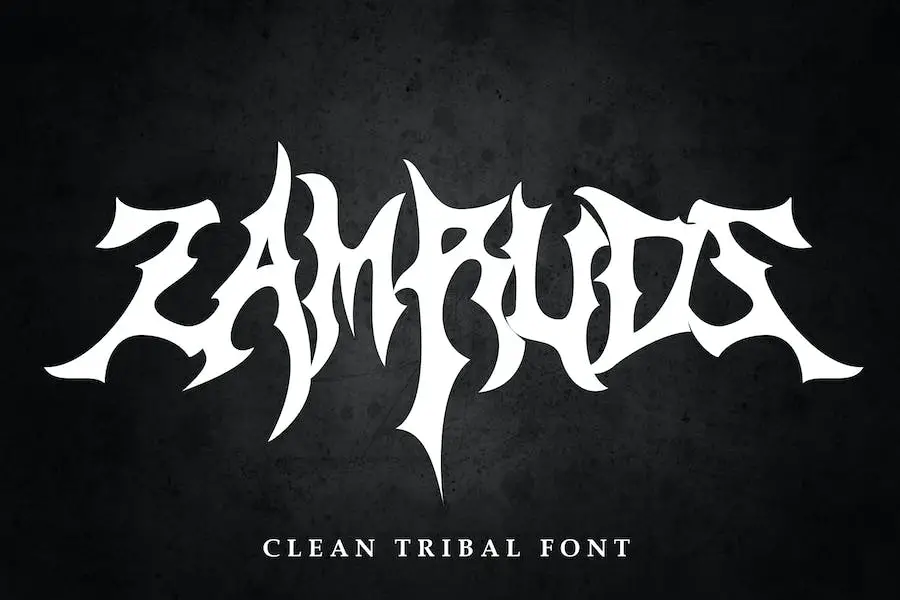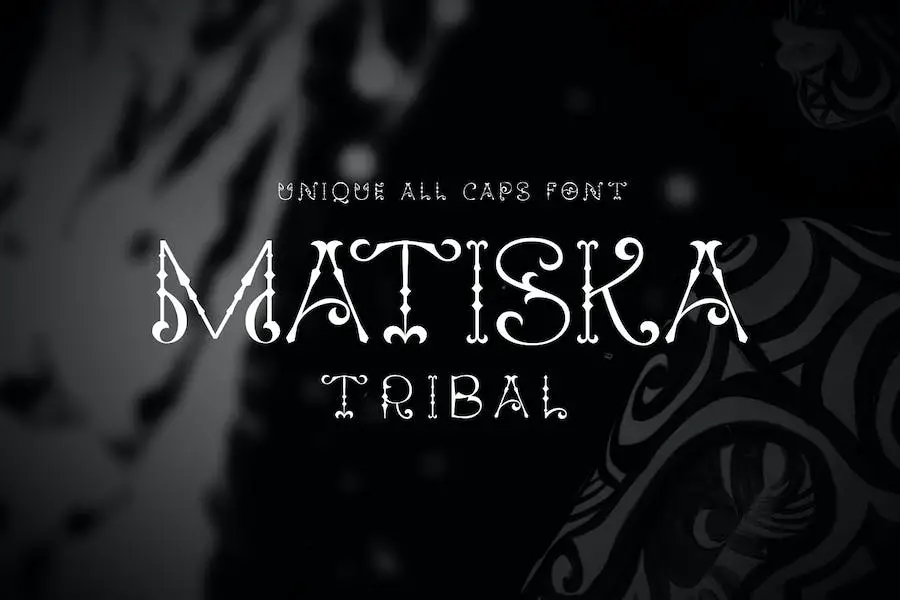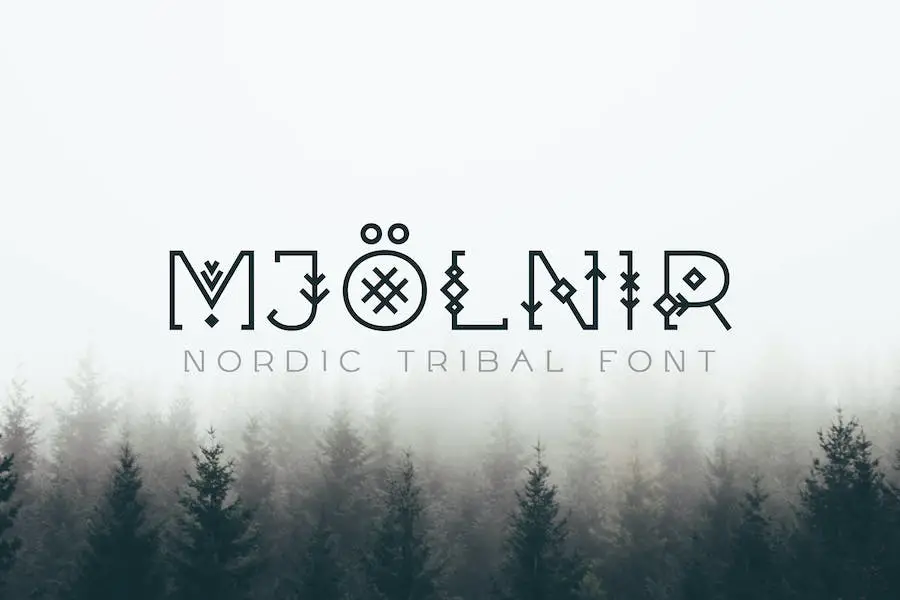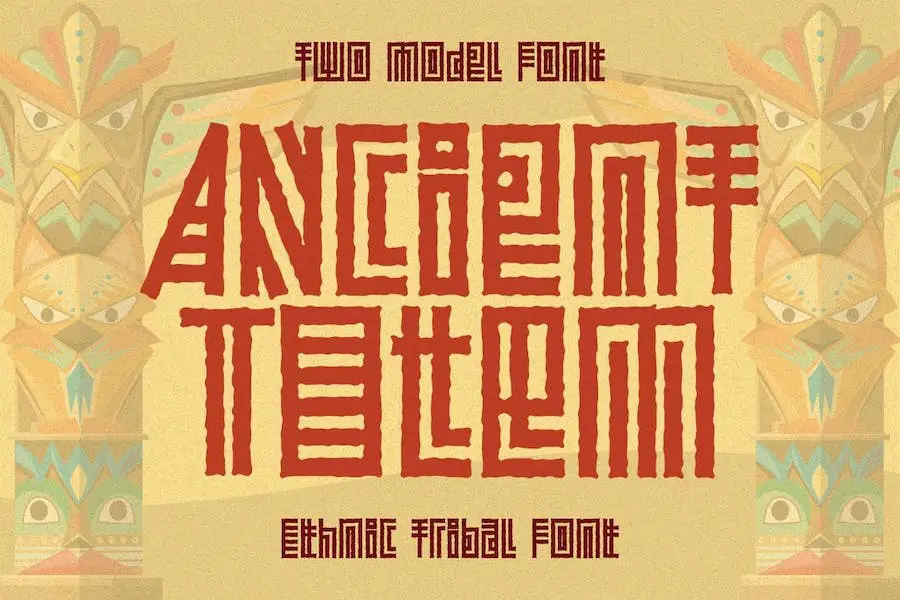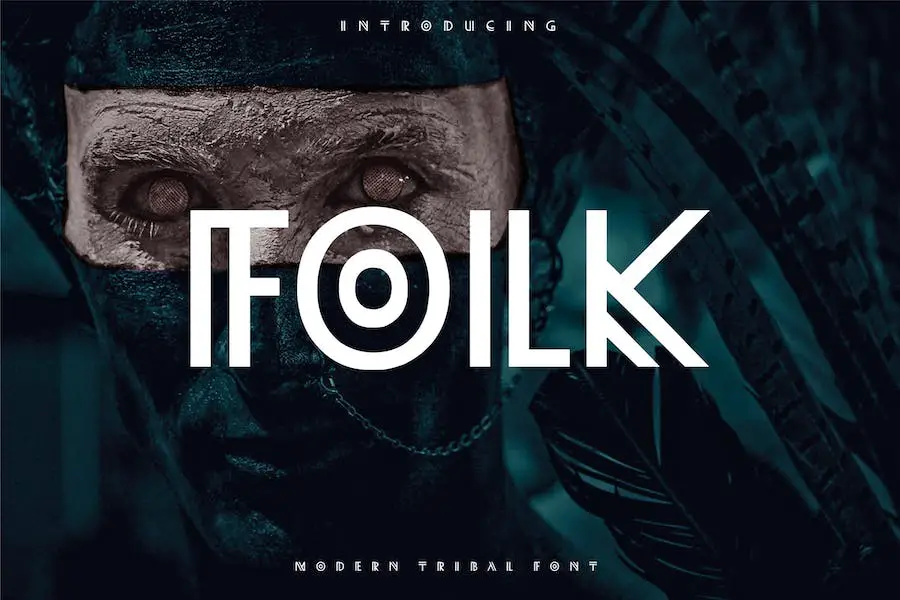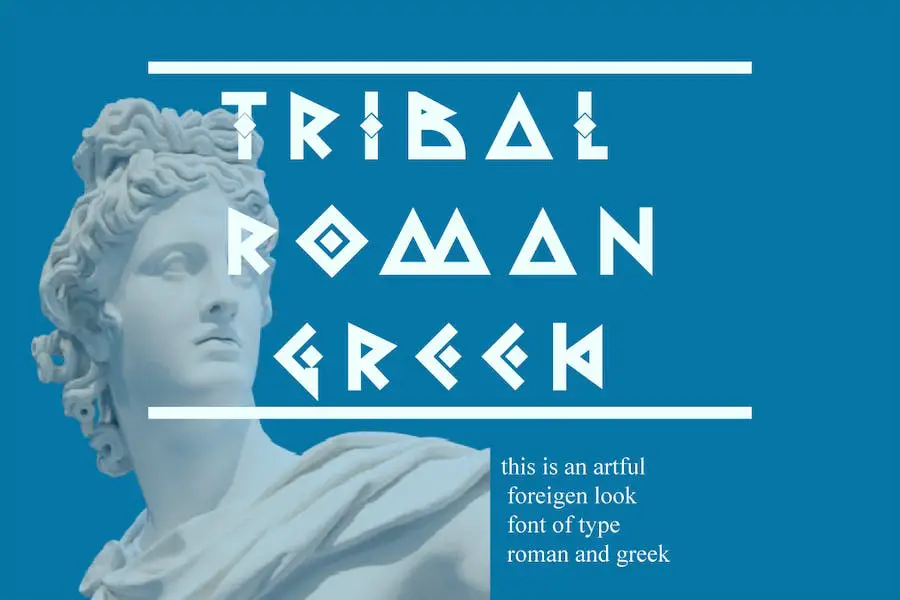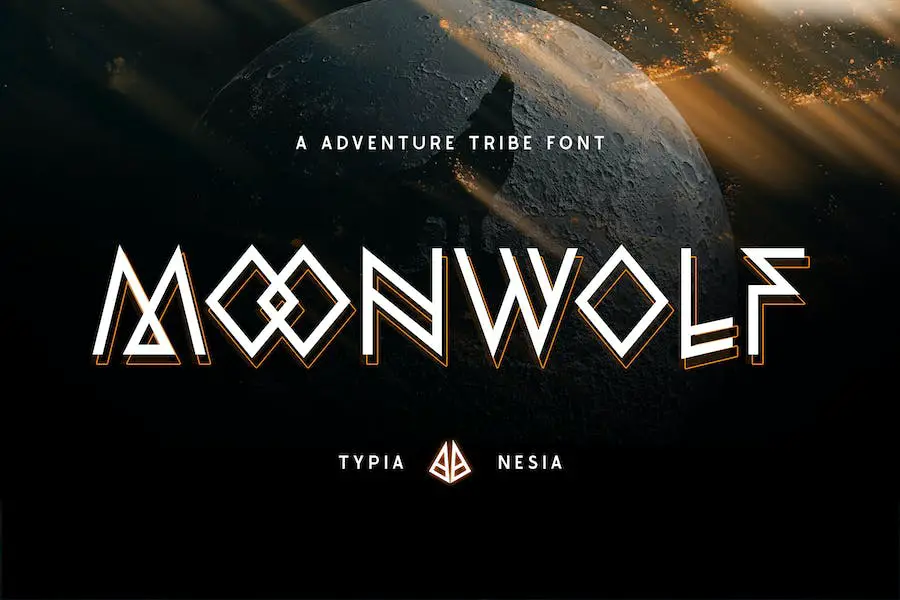
Cele mai bune 21 de fonturi tribale 2023 (gratuit și premium)
Publicat: 2023-09-05Sunteți un designer grafic în căutarea fontului tribal perfect pentru a vă îmbunătăți proiectele? Nu mai căuta! În această postare pe blog, vom împărtăși cele mai bune 21 de fonturi tribale care vă vor duce designul la următorul nivel.
Dar înainte de a ne arunca, s-ar putea să vă întrebați, de ce fonturi tribale? Ei bine, fonturile tribale adaugă o notă unică și captivantă oricărui design. Sunt perfecte pentru a crea un aspect îndrăzneț și dinamic, cu modelele lor complicate și elementele de inspirație tribală.
Deci, dacă sunteți gata să explorați lumea fonturilor tribale, să începem!
Acum, să vorbim despre ce vă puteți aștepta de la această postare pe blog. Am pregătit o listă cu cele mai bune 21 de fonturi tribale care vă vor inspira cu siguranță și vă vor ridica proiectele de design.
Fiecare font a fost atent selectat pe baza atractivității sale vizuale, versatilității și popularității în rândul designerilor grafici. Deci, puteți avea încredere că aceste fonturi au fost încercate și testate de profesioniști din industrie.
În acest articol, nu vă vom prezenta doar fonturile, ci vă vom oferi și câteva fapte și statistici interesante despre fiecare. Veți afla despre originile lor, inspirația din spatele designurilor lor și cum pot fi folosite pentru a crea imagini uimitoare.
Așadar, pregătește-te să descoperi lumea fonturilor tribale și să-l găsești pe cel perfect pentru următorul tău proiect. Să sărim direct în primul font de pe lista noastră și să lăsăm creativitatea să curgă!
Cele mai bune fonturi tribale premium
Doriți să vă îmbunătățiți proiectele de design? Nu căutați mai departe decât compilația noastră cu cele mai bune 21 de fonturi tribale! În această secțiune, vă prezentăm cele mai bune opțiuni premium care sunt garantate pentru a vă îmbunătăți eforturile creative.
Așa că haideți, verificați următoarele produse și duceți-vă modelele la nivelul următor!
Font tribal
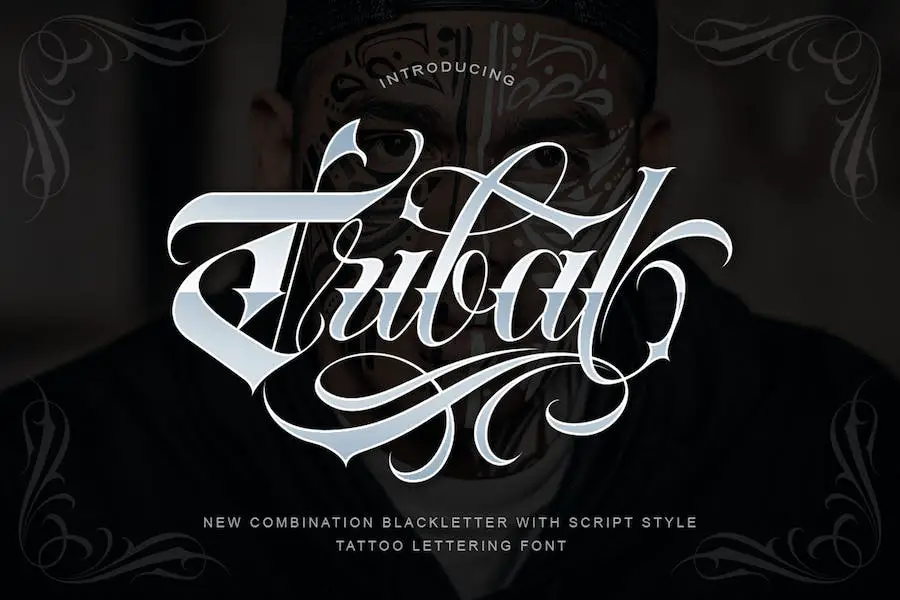
Fontul Tribal este un font unic și versatil, care combină aspectul îndrăzneț și îndrăzneț al Blackletter cu eleganța stilului Script.
Acest font este conceput special pentru modele de tatuaje, studiouri de logo, modele de cămăși, postere și proiecte de branding. Este perfect pentru a adăuga o notă tribală proiectelor tale de design grafic.
Cu Fontul Tribal, puteți crea modele captivante de tatuaje care îmbină tradiția și modernitatea. Formele complicate de litere adaugă profunzime și caracter oricărui tatuaj, făcându-l o piesă de artă remarcabilă.
Indiferent dacă proiectați o mânecă tribală sau un mic tatuaj la încheietura mâinii, acest font vă poate aduce viziunea la viață.
Studiourile de logo pot beneficia și de Fontul Tribal. Aspectul său puternic și îndrăzneț îl face ideal pentru crearea de logo-uri memorabile și atrăgătoare. Puteți încorpora cu ușurință elemente de artă tribală în designul logo-ului dvs., adăugând o notă unică și distinctivă branding-ului clienților dvs.
Burowai
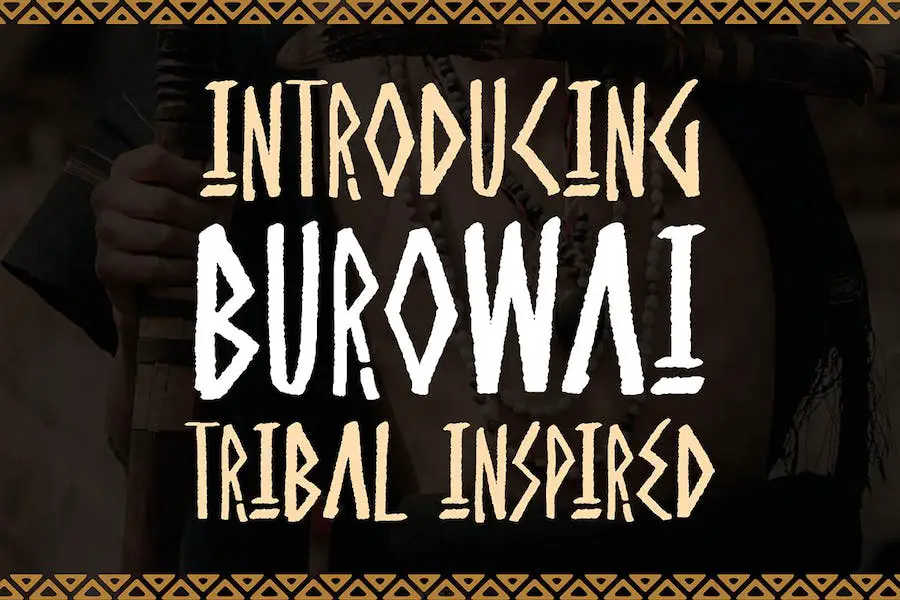
Burowai este un font incredibil care întruchipează vibrațiile antice și tribale. Inspirându-se din literele grecești antice și ornamentele tribale, acest font prezintă frumusețea desenelor etnice.
Cu combinația sa unică de forme asemănătoare ramurilor de copac și liniile aspre similare cu inscripțiile antice peșteri, Burowai este perfect pentru proiecte centrate pe teme naturale, artă populară, estetică tribală, design pentru copii, aventuri și mișcări sociale.
Detaliile complexe și sentimentul autentic al lui Burowai îl fac o alegere remarcabilă pentru designerii grafici care doresc să-și îmbunătățească proiectele cu o notă de moștenire culturală.
Indiferent dacă lucrați la un afiș promoțional, un banner pentru site-ul web, un design de marfă sau orice alt efort creativ, Burowai vă va ridica munca și vă va captiva publicul.
Versatilitatea lui Burowai îi permite să fie încorporat perfect în diverse proiecte și stiluri de design. Aspectul său organic și rustic adaugă o notă fermecătoare și autentică, aducând un sentiment de profunzime și unicitate design-urilor dumneavoastră.
Gasmyn
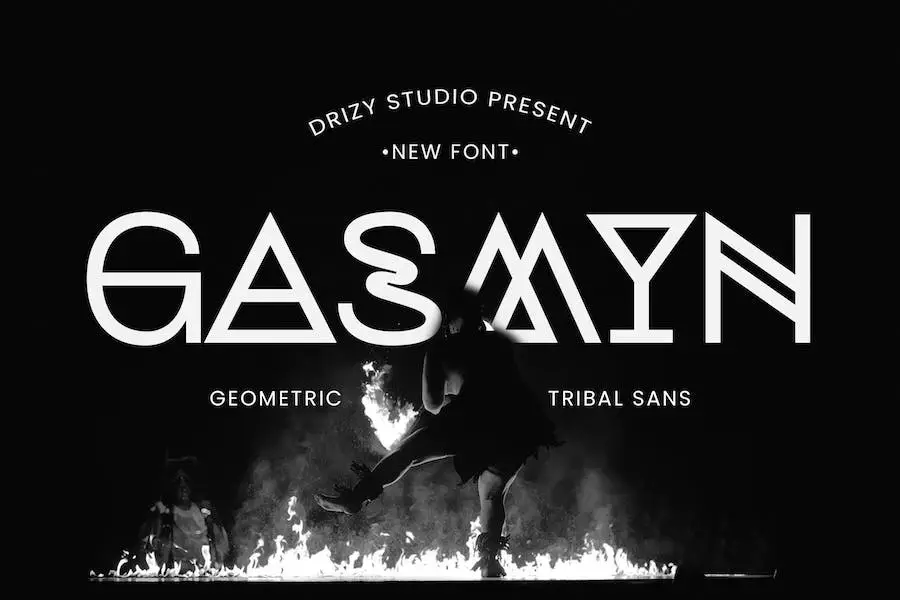
Gasmyn este un font geometric tribal de la studioul Drizy. Este perfect pentru designerii grafici care doresc să-și îmbunătățească proiectele cu o temă etnică unică. Cu toate stilurile esențiale de care aveți nevoie, Gasmyn este un must-have pentru a crea modele uimitoare care ies în evidență.
Acest font tribal este proiectat cu precizie, permițându-vă să obțineți un aspect curat și profesional. Formele sale geometrice și detaliile complicate oferă design-urilor tale o notă de autenticitate culturală, făcându-le izbitoare și captivante din punct de vedere vizual.
Gasmyn oferă o gamă largă de stiluri, asigurându-vă că veți găsi potrivirea perfectă pentru orice proiect. Indiferent dacă lucrați la un poster, logo sau grafică pentru rețelele de socializare, acest font vă oferă acoperire.
Vă mulțumim pentru timpul acordat citirii articolului nostru. Sperăm că ți-a oferit informații și inspirație valoroase.